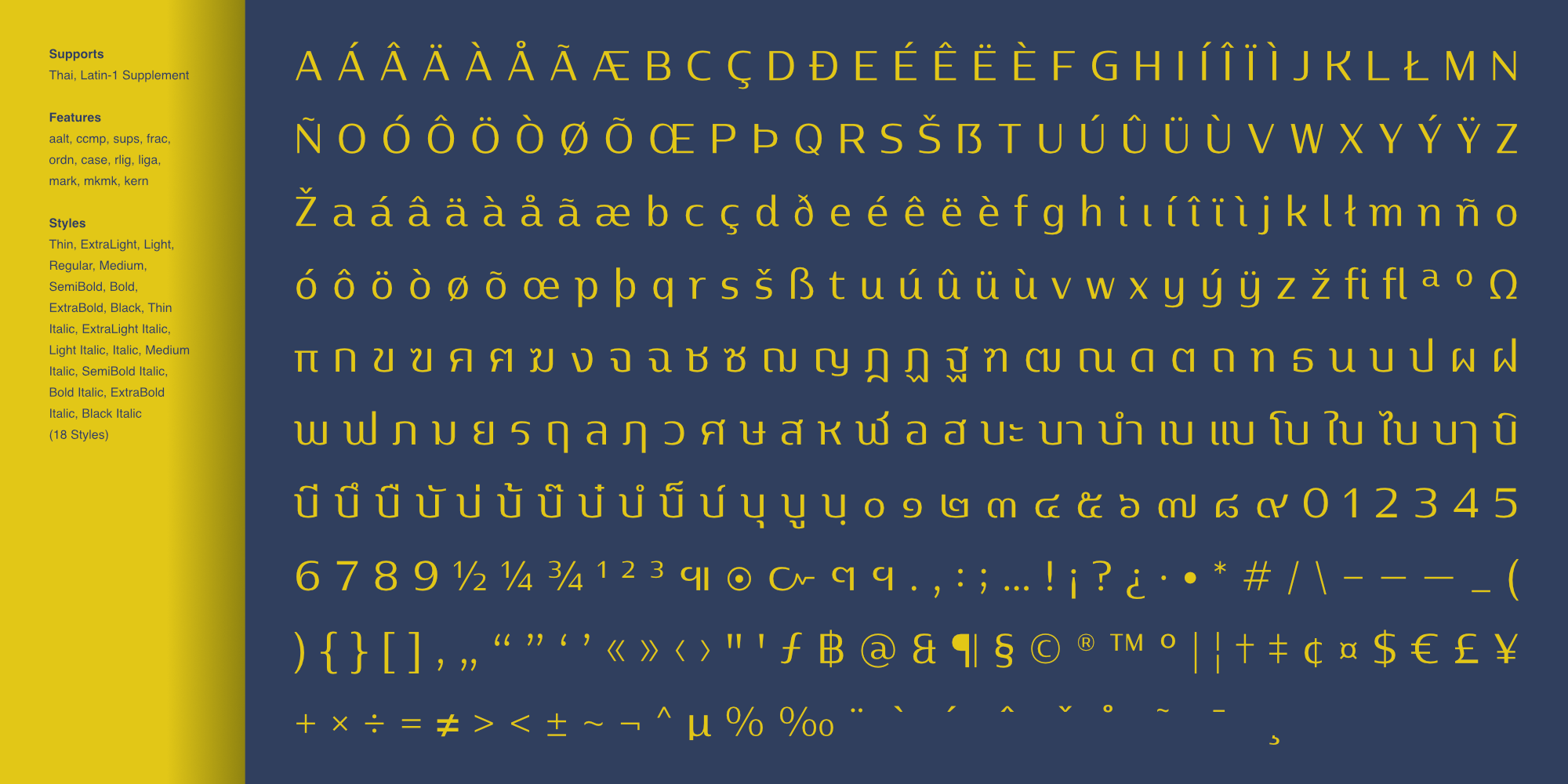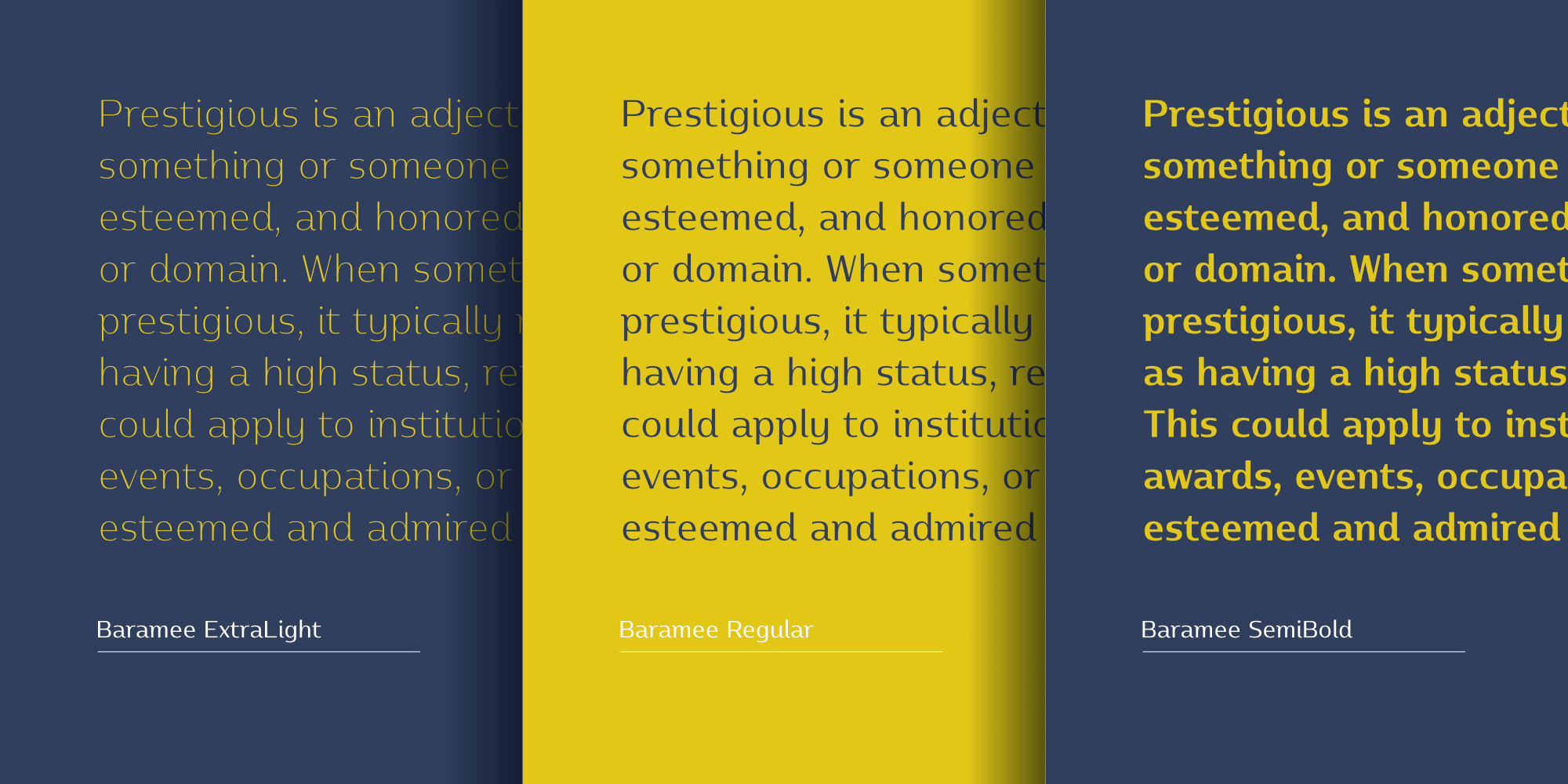
บารมี | Baramee
ชื่อฟอนต์ : บารมี | Baramee
Baramee เป็นอักษรแบบแซนเซอริฟ โดยที่เส้นแนวนอนมีความหนาครึ้งหนึ่งของเส้นแนวตั้งทำให้เกิดความเปรียบต่างขึ้นแต่ไม่มากจนเกินไป ปลายหัวของตัวอักษร (Terminal) เป็นตัดตรงในแนวตั้ง ตัวอักษรไทยมีการยิบยืมรูปแบบเดือย (Spur) ของตัวละตินมาทำเป็นหัวของตัวอักษร ส่งผลให้โดยภาพรวมรู้สึกได้ถึง ความภูมิฐาน ดูมี "บารมี" ในขณะเดียวกันก็ให้ความรู้สึกร่วมสมัย  ซึ่งมีให้เลือกใช้ถึง 18 สไตล์ รองรับตัวอักษรลาติน 1 และอักษรไทย เหมาะสำหรับสิ่งพิมพ์ต่าง ๆ ทั้งออนไลน์และออฟไลน์ ที่เน้นในเรื่องความภูมิฐาน บารมี สิริมงคล